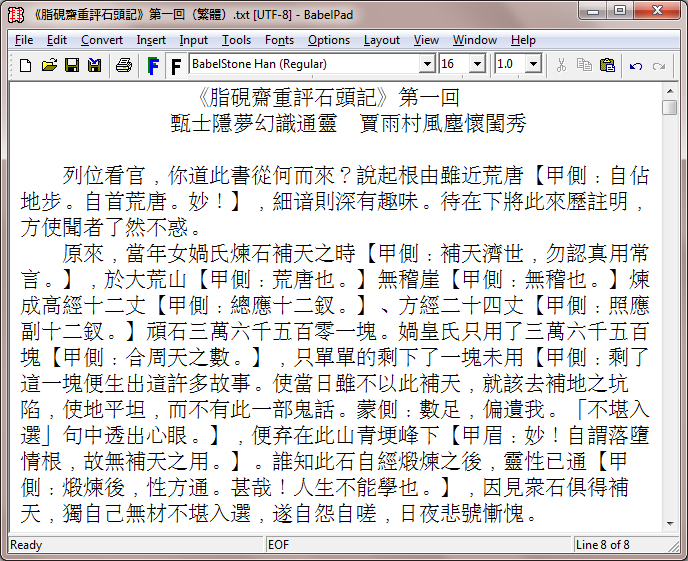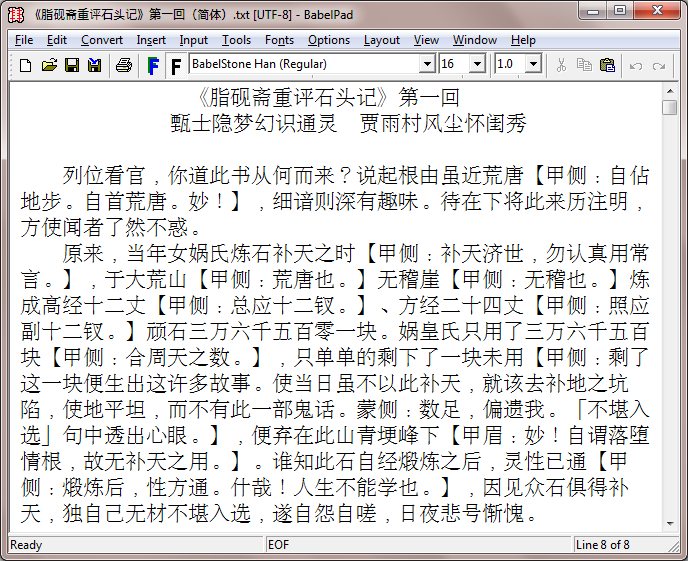
巴貝斯通漢(BabelStone Han ),是一種免費的Unicode CJK字體,具有41,000多個漢字(hanzi,kanji,hanja),總共超過52,000個Unicode字符。它是一種宋體/明體(Song / Ming)風格的字體,其字形以中華人民共和國使用的正式字符形式為原型。它涵蓋了繁體漢字和簡體漢字,並且包括許多大多數CJK字體中找不到的稀有或古舊字符,以及用於書寫壯語的上千個Sawndip字符。在專用區(PUA)中還包括3,700多個未編碼的漢字。該字體正在不斷開發中,因為在接下來的幾年中,數以萬計的CJK表意文字計劃被納入Unicode。
繁體中文樣本
簡體中文樣本